這裡整理了一些容易閱讀的等寬英文字型,適合程式設計師在編寫程式時使用。
一般程式設計師在撰寫程式時,通常都會需要閱讀大量的程式碼,為自己的開發環境選擇一個適合閱讀的字型,是一件很重要的事情。
以下整理了各種適合程式設計的等寬字型(Monospaced Font),在 Ubuntu Linux 中使用 Vim 編輯器測試的結果。
Terminus
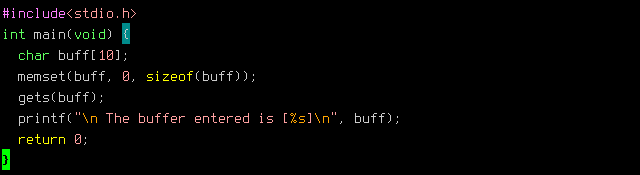
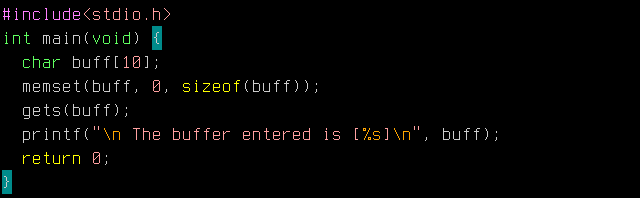
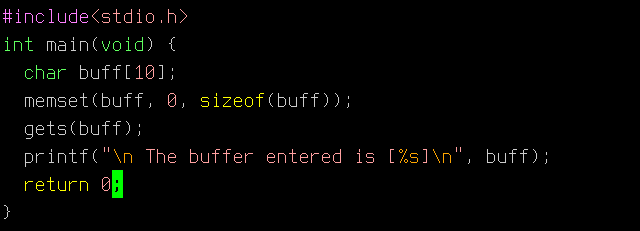
字型名稱:Terminus
Envy Code R
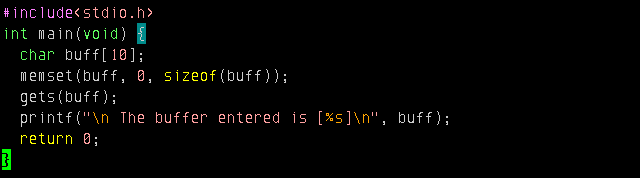
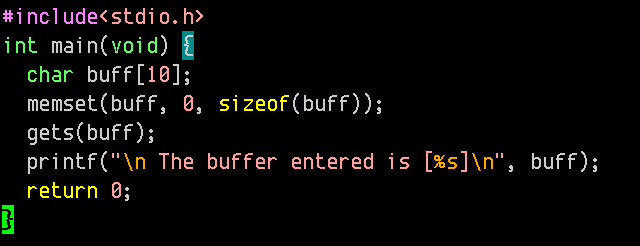
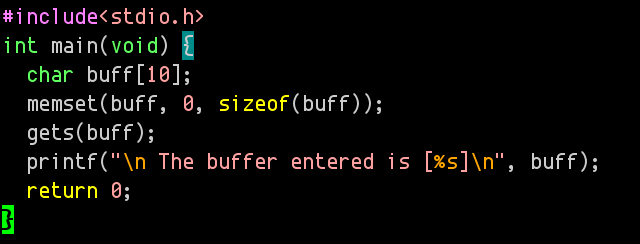
字型名稱:Envy Code R
Hermit Medium
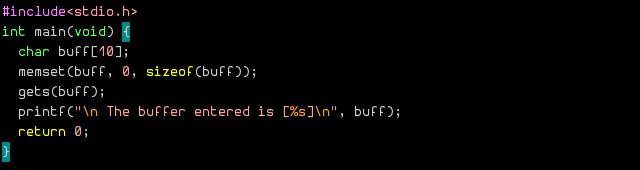
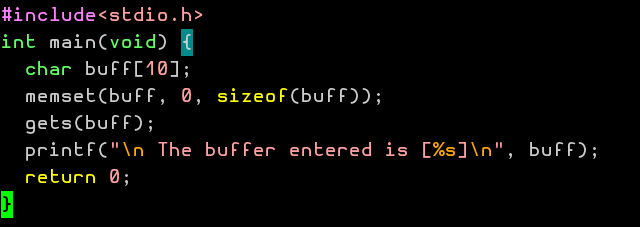
字型名稱:Hermit
Inconsolata
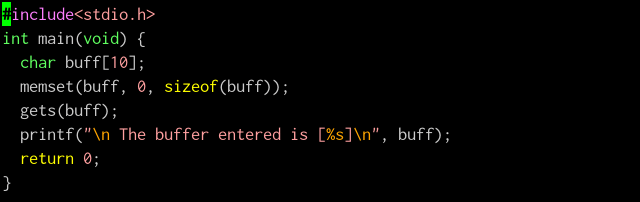
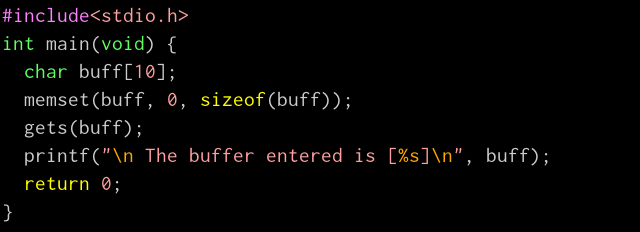
字型名稱:Inconsolata
Deja Vu Sans Mono
字型名稱:Deja Vu Sans Mono
Elronet Monospace
字型名稱:Elronet Monospace
Anonymous Pro
字型名稱:Anonymous Pro
Profont
字型名稱:Profont
AR PL UMing TW
字型名稱:AR PL UMing
Monofur
字型名稱:Monofur
Courier Negreta
Courier 是一個各種系統都會內建的字型,不需要安裝即可使用,有些系統中會以 Courier New 這個名稱表示該字型。上面的兩張圖是將樣式調整為 Negreta 的情況。
Monaco
字型名稱:Monaco
Proggy Clean
字型名稱:Proggy Clean
Droid Sans Mono
字型名稱:Droid Sans Mono
Consolas
Consolas 是微軟所設計的字型,不過現在許多系統都已經有內建了。
字型名稱:Consolas
Dina
字型名稱:Dina
Source Code Pro
Source Code Pro 是由 Paul D. Hunt 所設計的開放原始碼字型。
字型名稱:Source Code Pro
Bitstream Vera Sans Mono
字型名稱:Bitstream Vera Sans Mono